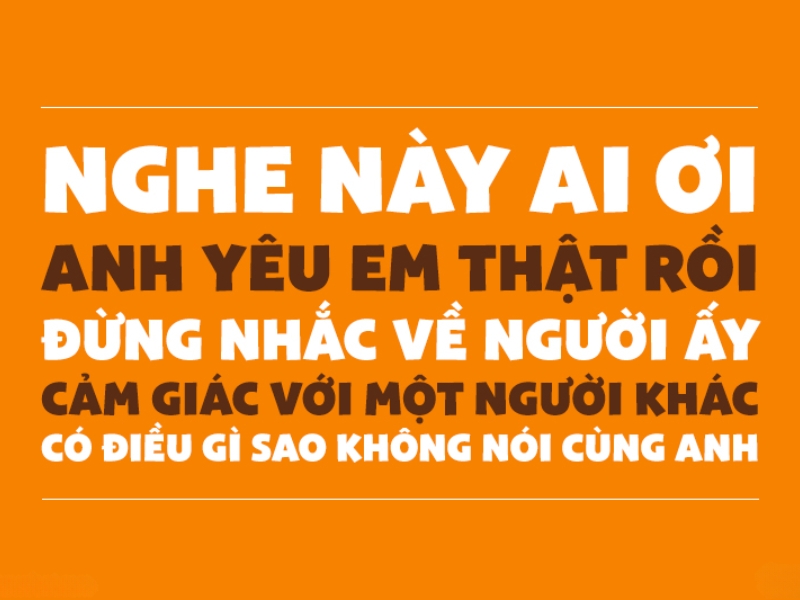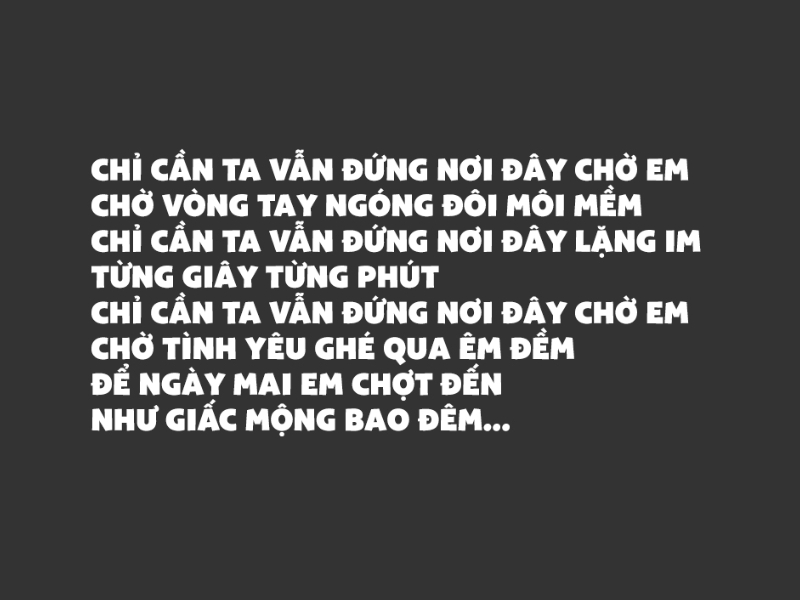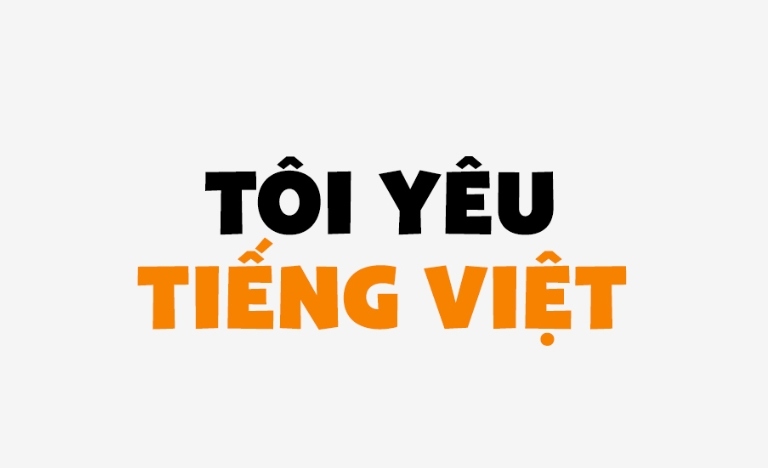
Font SVN Bango Việt hóa là kiểu chữ tròn trịa, dày dặn, mang phong cách vui nhộn, trẻ trung và rất dễ thu hút ánh nhìn. Phiên bản Việt hóa hỗ trợ đầy đủ dấu tiếng Việt, chuẩn Unicode, đảm bảo hiển thị mượt mà trên cả thiết kế kỹ thuật số lẫn in ấn.
Font thích hợp cho poster, banner, bao bì, logo hay nội dung mạng xã hội, giúp thiết kế trở nên nổi bật, thân thiện và đồng bộ thương hiệu. Trong bài viết này, In Viva cung cấp bộ sưu tập font chữ brush việt hóa miễn phí với đầy đủ định dạng TTF, OTF phù hợp cho thiết kế và in ấn chuyên nghiệp.
Font SVN Bango việt hóa nổi bật với kiểu chữ tròn trịa, vui nhộn, phù hợp cho các thiết kế mang tính trẻ trung như poster, banner, bao bì hoặc nội dung mạng xã hội. Phiên bản việt hóa hỗ trợ đầy đủ dấu tiếng Việt, giúp bạn sử dụng dễ dàng mà không lo lỗi font. Dưới đây là 5 phiên bản font SVN Bango Việt hóa phổ biến, hay được sử dụng nhất:
| Phiên bản font | Đặc điểm | Ứng dụng |
| SVN Bango Regular | Nét chữ tròn, đều, vui nhộn | Poster, tiêu đề, banner |
| SVN Bango Bold | Nét đậm, nổi bật | Quảng cáo, tiêu đề lớn |
| SVN Bango Outline | Dạng viền, sáng tạo | Thiết kế sáng tạo, typography |
| SVN Bango Shadow | Có hiệu ứng đổ bóng | Poster, banner thu hút |
| SVN Bango Stylized | Biến thể cách điệu | Logo, thiết kế độc đáo |
Đặc điểm nổi bật của font SVN Bango Việt hóa
Font SVN-Bango Việt hóa là lựa chọn hoàn hảo cho những thiết kế cần sự vui nhộn, nổi bật và thân thiện. Với nét chữ béo, tròn trịa cùng phong cách hoạt hình retro hiện đại, font này không chỉ dễ đọc mà còn tạo ấn tượng thị giác mạnh, mang lại năng lượng tích cực cho mọi sản phẩm.
- Phong cách thiết kế: Kiểu dáng béo (bold/chunky), các góc bo tròn mềm mại nhưng vẫn chắc chắn. Mang đậm hơi hướng hoạt hình (cartoon) kết hợp phong cách retro hiện đại, tạo cảm giác vui nhộn và năng lượng tích cực.
- Mục đích sử dụng: Phù hợp làm tiêu đề lớn (display font), poster, biển hiệu, bao bì sản phẩm, game, ấn phẩm cho trẻ em hoặc bất kỳ thiết kế sáng tạo nào cần sự nổi bật.
- Đặc điểm Việt hóa: Được nhóm SVN Fonts Việt hóa cẩn thận, hỗ trợ đầy đủ dấu tiếng Việt, chuẩn Unicode, đảm bảo không lỗi font khi sử dụng trên các phần mềm thiết kế.
- Tính năng nổi bật: Tạo cảm giác thân thiện, vui tươi, tràn đầy năng lượng tích cực; dễ đọc ngay cả ở kích thước lớn.
- Ấn tượng thị giác: Nét chữ to, tròn trịa, tạo hiệu ứng mạnh, giúp thiết kế trở nên độc đáo và cá tính, nhưng vẫn giữ sự vững chãi, không cứng nhắc.
Ứng dụng của font SVN Bango
Font SVN Bango Việt hóa được sử dụng rộng rãi trong nhiều lĩnh vực:
- Thiết kế poster, banner quảng cáo
- Bao bì sản phẩm, đặc biệt là sản phẩm cho giới trẻ
- Thiết kế logo thương hiệu vui nhộn, sáng tạo
- Nội dung mạng xã hội (Facebook, TikTok, Instagram)
- Thiết kế ấn phẩm cho trẻ em hoặc sự kiện giải trí
5 lưu ý khi sử dụng font SVN Bango Việt hóa
Khi sử dụng font SVN Bango Việt hóa, bạn cần lưu ý một số điểm quan trọng để đảm bảo tính thẩm mỹ và hiệu quả truyền thông. Đây là bộ font có đường nét dày, bo tròn và mang phong cách retro vui nhộn nên cực kỳ thu hút thị giác khi làm tiêu đề hoặc các thiết kế quảng cáo trẻ trung.
- Nên tận dụng đặc điểm nét chữ đậm để làm nổi bật các từ khóa chính hoặc tiêu đề lớn trên banner và poster.
- Tránh sử dụng font này cho các đoạn văn bản dài hoặc nội dung chi tiết vì độ dày của chữ sẽ gây cảm giác nặng nề và khó đọc cho người xem.
- Kết hợp khéo léo với các font chữ không chân hiện đại và thanh mảnh hơn để tạo sự cân bằng và giúp bố cục thiết kế trở nên hài hòa.
- Chú ý điều chỉnh khoảng cách giữa các chữ cái (kerning) hợp lý để các nét chữ lớn không bị dính vào nhau gây mất thẩm mỹ.
- Luôn kiểm tra kỹ các dấu tiếng Việt để đảm bảo bản Việt hóa hoạt động ổn định và không bị lỗi hiển thị trong quá trình thiết kế các ấn phẩm quà tặng doanh nghiệp.
Font SVN Bango Việt hóa có dùng cho in ấn được không?
Làm sao chọn phiên bản font phù hợp?
- Regular: chữ đều, vui nhộn, dùng cho tiêu đề nhỏ hoặc nội dung mạng xã hội.
- Bold: chữ đậm, nổi bật, dùng cho tiêu đề lớn hoặc quảng cáo.
- Outline / Shadow / Stylized: dùng cho thiết kế sáng tạo, logo hoặc poster nổi bật.